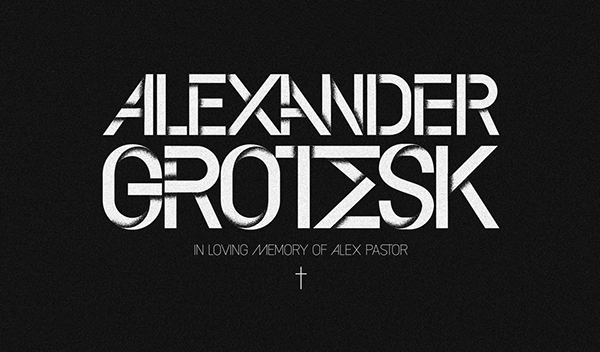
A “Alexander Grotesk Font Family” é uma elegante tipografia geométrica que se destaca por sua simplicidade e modernidade. Ideal para trabalhos visuais diversos, como logotipos, textos, apresentações, cartazes, revistas, avisos, títulos, cartões de visita, design web, convites, cabeçalhos e identificações empresariais. Foi projetada pelo designer Joan Ramon Pastor e concebida para se adequar a um amplo leque de aplicações visuais, tornando-se uma opção versátil em sua categoria. A “Alexander Grotesk Font Family” é uma fonte que traz ao design gráfico um toque clean e contemporâneo, sem perder a personalidade necessária para qualquer projeto profissional.